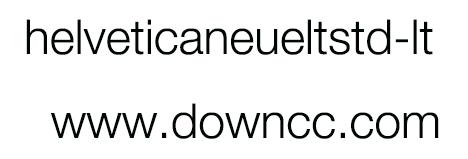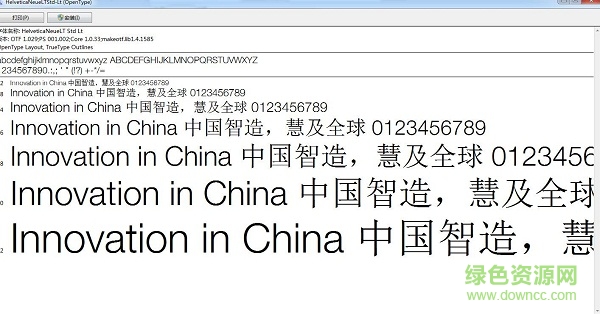
helveticaneueltstd-lt字體是一款普通的無襯線字體,簡潔干凈易辨識,可以廣泛應(yīng)用于排版印刷、網(wǎng)站、廣告、影視、雜志期刊等領(lǐng)域,需要這類字體的朋友快來下載吧!
整體感受是簡潔、清晰,沒有手工感,非常冷靜的字體!
1.切口齊平,筆畫始終以水平或垂直收尾
2.頂端平坦
3.方形點(diǎn)